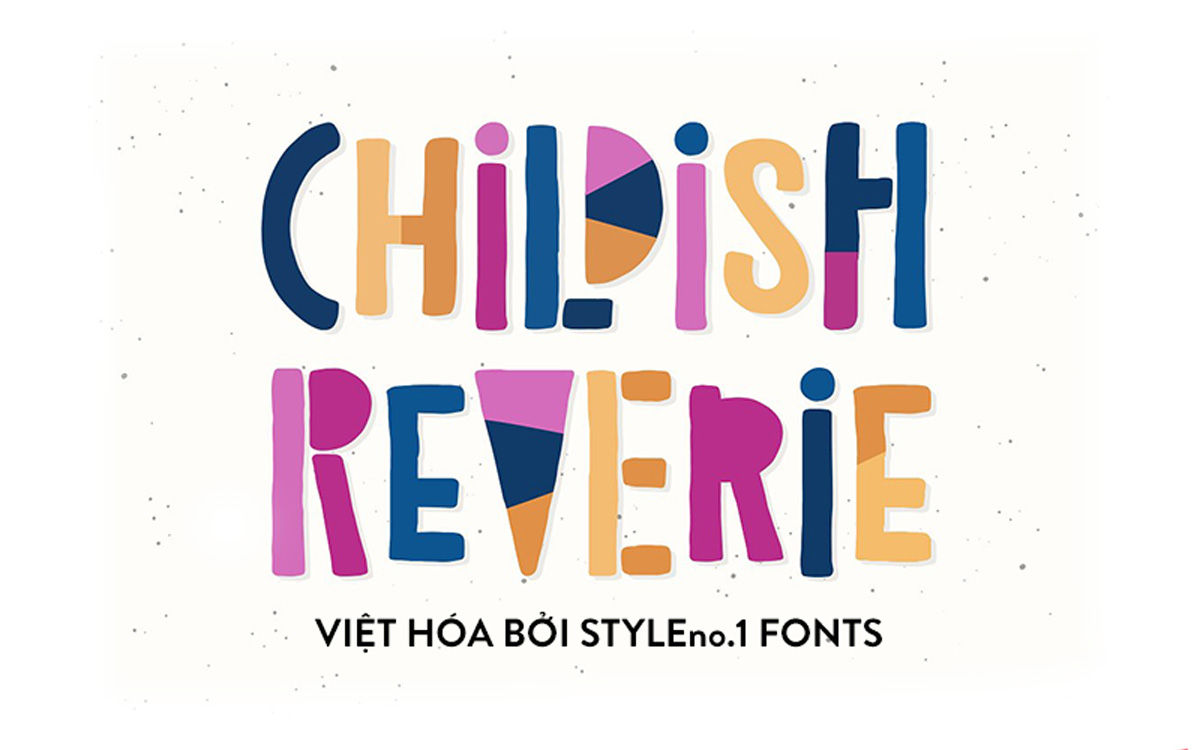
Font chữ vui vẻ, dễ thương, hoạt hình cho lĩnh vực trẻ em, đồ ăn, fodd, cute SVN-Childish Reverie Doodles
Trong thế giới thiết kế đồ họa hiện đại, việc lựa chọn một bộ font chữ phù hợp đóng vai trò vô cùng quan trọng trong việc truyền tải cảm xúc và thông điệp của thương hiệu đến với khách hàng. Đặc biệt đối với các dự án hướng tới đối tượng trẻ em, ngành thực phẩm đồ ăn nhanh hay các sản phẩm mang phong cách đáng yêu, một phông chữ nét vẽ ngộ nghĩnh sẽ tạo nên sự khác biệt vượt trội. Font chữ SVN-Childish Reverie Doodles chính là sự kết hợp hoàn hảo giữa nét chữ bay bổng, vui tươi và hệ thống hình vẽ doodle độc đáo, mang đến diện mạo vô cùng sống động cho mọi sản phẩm truyền thông.
Font Chữ Vui Vẻ, Dễ Thương, Hoạt Hình Cho Lĩnh Vực Trẻ Em, Đồ Ăn, Food, Cute SVN-Childish Reverie Doodles – Sự Lựa Chọn Thiết Kế Đỉnh Cao
Khi bắt tay vào sáng tạo các sản phẩm thương mại dành cho trẻ em hay ngành thực phẩm F&B, nhà thiết kế thường phải đối mặt với thách thức làm sao để thu hút sự chú ý ngay từ cái nhìn đầu tiên. Những kiểu chữ cứng nhắc, truyền thống hoàn toàn không phù hợp với không khí tươi vui, hồn nhiên mà các thương hiệu này muốn hướng tới. Sự xuất hiện của bộ font SVN-Childish Reverie Doodles đã giải quyết triệt để vấn đề này, mang lại một làn gió mới tràn đầy năng lượng tích cực, sự ngây thơ và nét hấp dẫn thị giác mạnh mẽ cho các tác phẩm thiết kế.
Các chức năng và đặc điểm nổi bật của font SVN-Childish Reverie Doodles
1. Phong cách thiết kế vẽ tay (Hand-drawn) hoạt hình ngộ nghĩnh và đầy cảm hứng
SVN-Childish Reverie Doodles sở hữu đường nét thiết kế phóng khoáng, tự do như những nét chữ ngô nghê, đáng yêu của trẻ thơ. Mọi đường cong, nét uốn lượn đều được trau dồi tỉ mỉ để tạo ra cảm giác tự nhiên nhất, xóa bỏ sự khô khan của các phông chữ kỹ thuật số thông thường. Khi áp dụng bộ font này vào các ấn phẩm truyền thông, bạn sẽ ngay lập tức truyền tải được sự ấm áp, gần gũi và niềm vui thích đến người xem, giúp thương hiệu dễ dàng chiếm trọn cảm tình của khách hàng mục tiêu.
2. Tối ưu hóa đặc biệt cho thiết kế thương hiệu trẻ em và giáo dục
Đối với các thương hiệu thời trang trẻ em, trường mầm non, trung tâm anh ngữ hay các nhà xuất bản sách thiếu nhi, SVN-Childish Reverie Doodles là một công cụ sáng tạo không thể thiếu. Font chữ này hỗ trợ đắc lực trong việc thiết kế bìa sách truyện, thẻ học thông minh (flashcard), bảng hiệu trường học, bao bì đồ chơi và các banner quảng cáo sự kiện dành cho thiếu nhi. Nét chữ vui nhộn giúp kích thích trí tưởng tượng phong phú và khả năng quan sát của trẻ nhỏ, biến mọi thông tin trở nên dễ tiếp thu và thú vị hơn bao giờ hết.
3. Sự lựa chọn hoàn hảo cho ngành F&B, đồ ăn vặt và thực phẩm (Food)
Trong ngành dịch vụ ăn uống F&B, đặc biệt là các quán trà sữa, tiệm bánh ngọt, quán ăn vặt hay thương hiệu thực phẩm cho gia đình, yếu tố thị giác đóng vai trò kích thích vị giác vô cùng lớn. SVN-Childish Reverie Doodles mang lại vẻ ngoài “ngon mắt”, ngọt ngào và năng động. Việc ứng dụng bộ font này lên menu, bao bì hộp giấy, ly cốc hay các bài đăng giới thiệu món ăn trên mạng xã hội sẽ giúp thương hiệu của bạn trở nên nổi bật, tạo cảm giác thân thiện và thôi thúc khách hàng trải nghiệm ngay lập tức.
4. Tích hợp bộ icon Doodles trang trí độc đáo và trọn bộ Tiếng Việt (Việt hóa)
Điểm cộng lớn nhất của SVN-Childish Reverie Doodles chính là việc đã được Việt hóa chỉn chu, hỗ trợ đầy đủ các dấu thanh Tiếng Việt mà không bị lỗi font hay mất tính thẩm mỹ. Bên cạnh bộ ký tự chữ cái chuẩn, phông chữ này còn đi kèm với bộ sưu tập các biểu tượng doodle vẽ tay cực kỳ đáng yêu như ngôi sao, trái tim, tia sáng, nét gạch chân hoạt hình… Điều này giúp các designer tiết kiệm hàng giờ đồng hồ tìm kiếm phần tử trang trí, chỉ cần gõ ký tự là đã có ngay những icon minh họa hoàn hảo cho thiết kế của mình.
5. Tính linh hoạt cao, tương thích trên nhiều nền tảng in ấn và kỹ thuật số
SVN-Childish Reverie Doodles được định dạng chuẩn xác, tối ưu hóa các điểm vector giúp phông chữ hiển thị sắc nét trên cả màn hình kỹ thuật số lẫn các ấn phẩm in ấn kích thước lớn. Dù bạn đang làm thumbnail YouTube, ảnh bìa Facebook, video TikTok, hay in ấn trên áo thun, ly sứ, bao bì sản phẩm, font chữ vẫn giữ nguyên độ mịn màng, không bị mờ hay vỡ nét. Sự linh hoạt này giúp quy trình làm việc của nhà thiết kế trở nên mượt mà và hiệu quả hơn rất nhiều.
Tầm quan trọng của việc chọn font chữ cute, hoạt hình trong chiến lược Marketing
Kiểu chữ không chỉ là phương tiện truyền tải ngôn ngữ mà còn là ngôn ngữ thị giác mạnh mẽ tác động đến tâm lý hành vi của người tiêu dùng. Sử dụng phông chữ vui nhộn, dễ thương như SVN-Childish Reverie Doodles giúp thương hiệu:
• Tạo sự khác biệt: Nổi bật giữa hàng ngàn đối thủ cạnh tranh đang sử dụng các bộ phông chữ tiêu chuẩn nhàm chán.
• Xây dựng thiện cảm: Tăng cường kết nối cảm xúc với đối tượng khách hàng là phụ huynh, trẻ em và giới trẻ thích sự cute.
• Tăng tỷ lệ tương tác: Các bài đăng mạng xã hội sở hữu hình ảnh sống động và typography ngộ nghĩnh luôn thu hút lượng like, share và comment cao hơn đáng kể.
• Bổ trợ nhận diện thương hiệu: Định hình một phong cách thương hiệu trẻ trung, năng động, thân thiện và đầy sáng tạo.